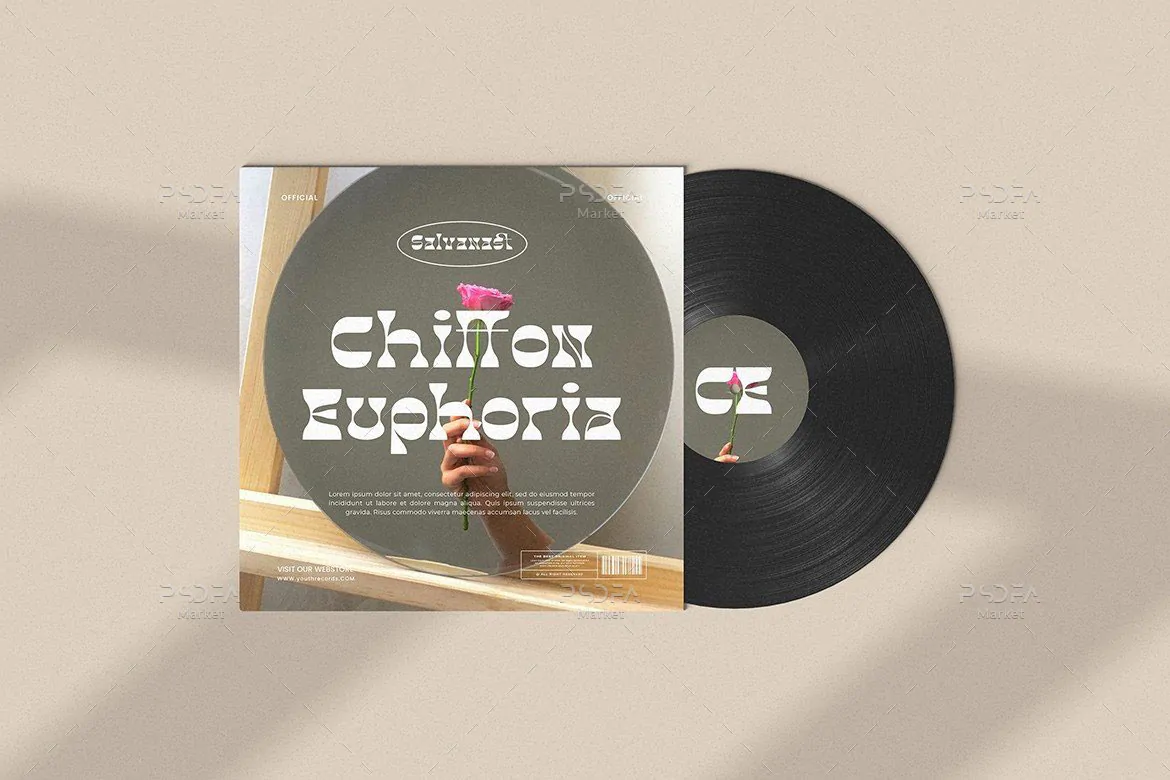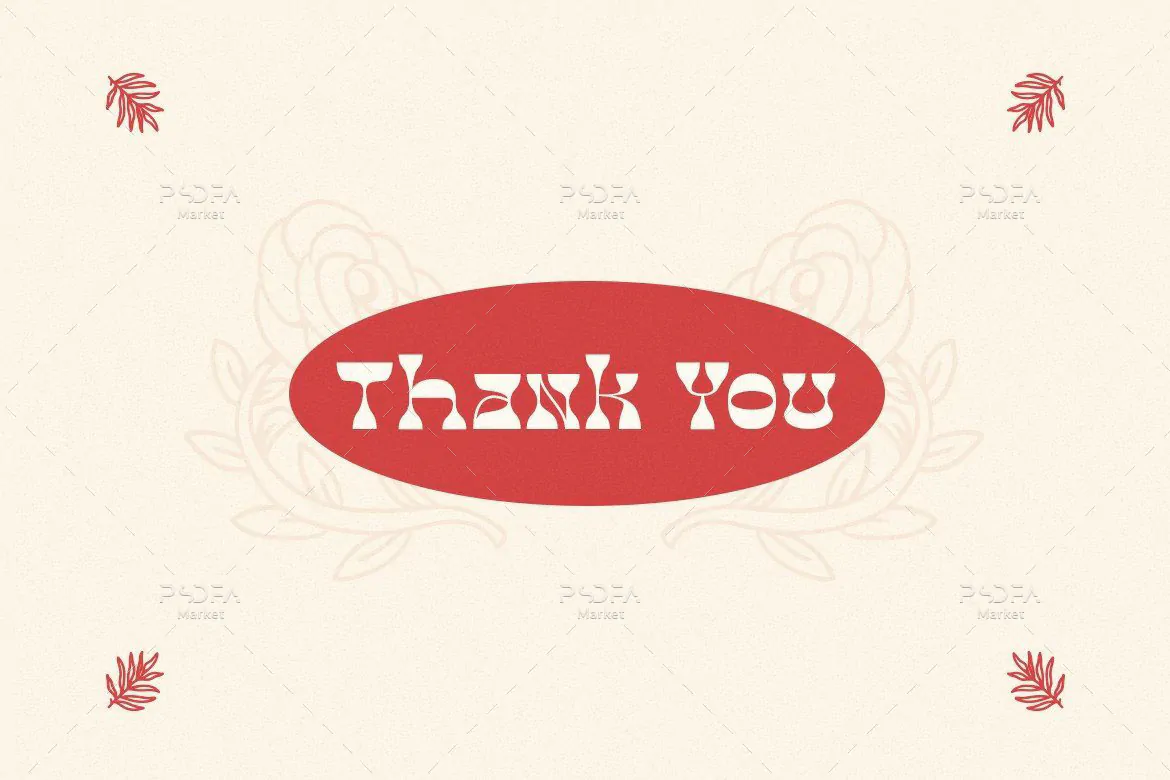
فونت مایع شکل Pacificles
فونت مایع شکل انگلیسی
فونت مایع شکل Pacificles یک قلم نمایشی فوق العاده زیبا انگلیسی است که میتوانید از آن در طرح و پروژههای گرافیکی مختلف به خصوص طراحی پوستر استفاده کنید. فونت Pacificles با وزن معمولی طراحی شده است که مناسب جهت استفاده در طراحی انواع پوستر، بسته بندی محصولات، ظروف یکبار مصرف، لوازم التحریر، تیشرت و … میباشد.